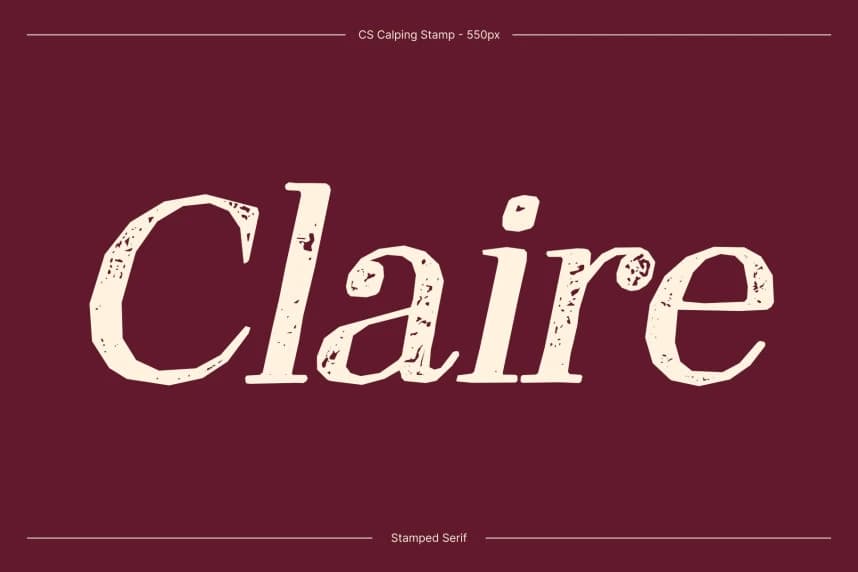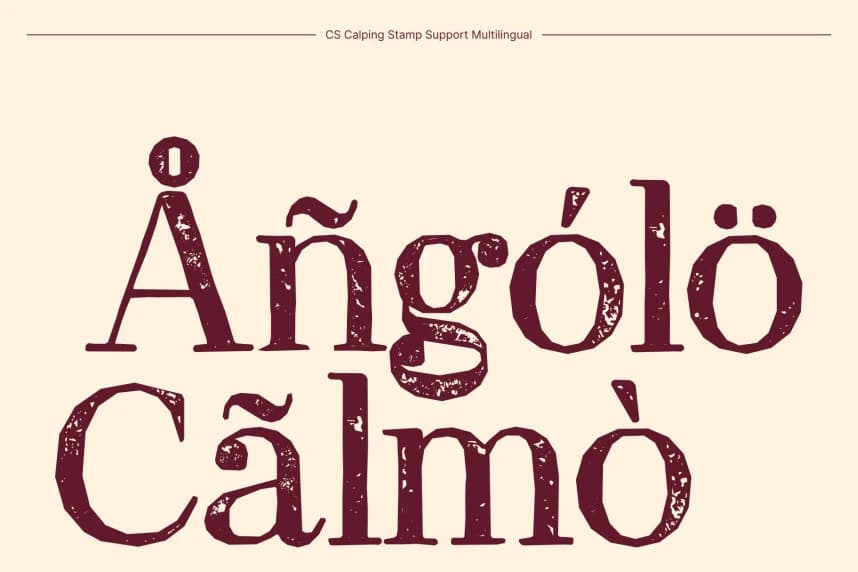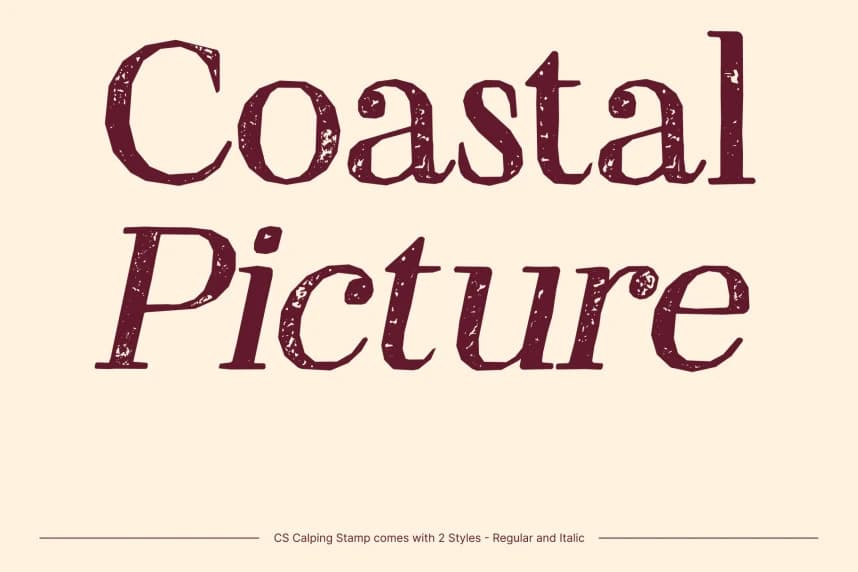
CS Calping Damga Yazı Tipi
CS Calping Stamp Font – Klasik Didone Serif ile Vintage Doku, Zamansız Zarafet ve Sanatsal Damga Karakteri. Bu, klasik zarafeti belirgin bir vintage damga etkisiyle birleştiren bir Didone serif fontudur.
CS Calping Stamp Font – Klasik Didone Serif, Vintage Doku ile Zamansız Zarafet ve Sanatsal Damga Karakteri. Bu, klasik zarafeti kendine özgü bir vintage damga etkisiyle birleştiren bir Didone serif fontudur.
CS Calping Stamp